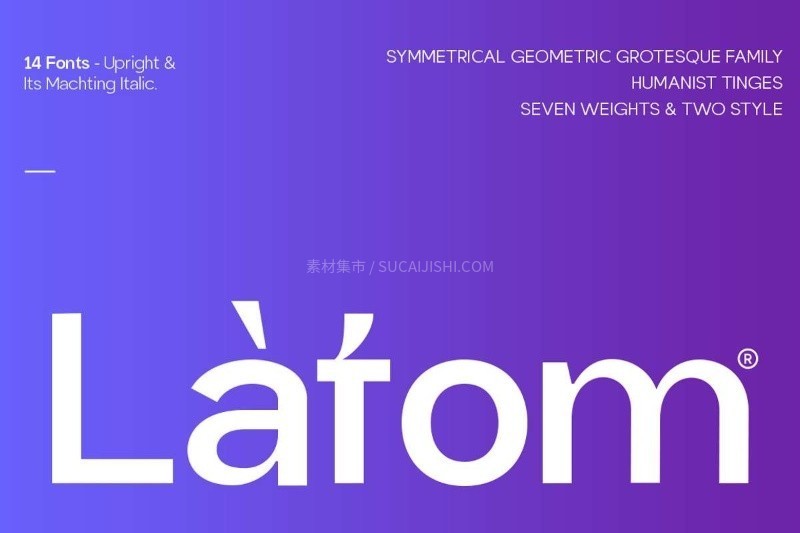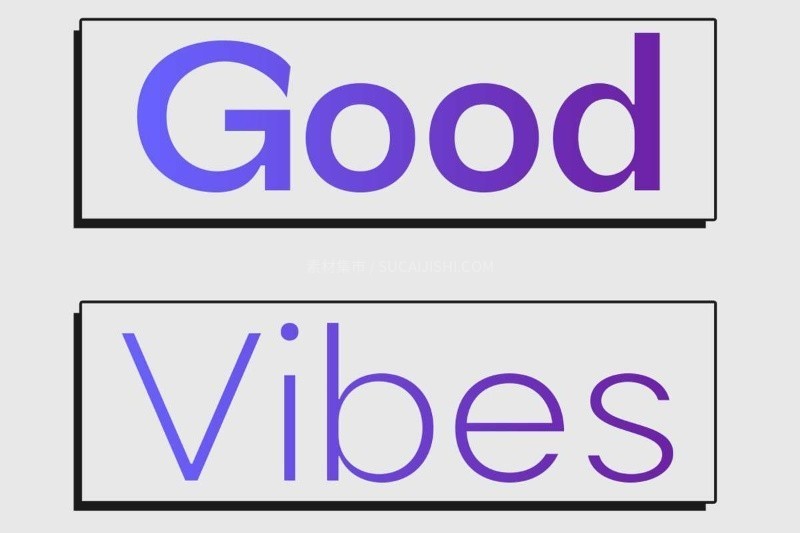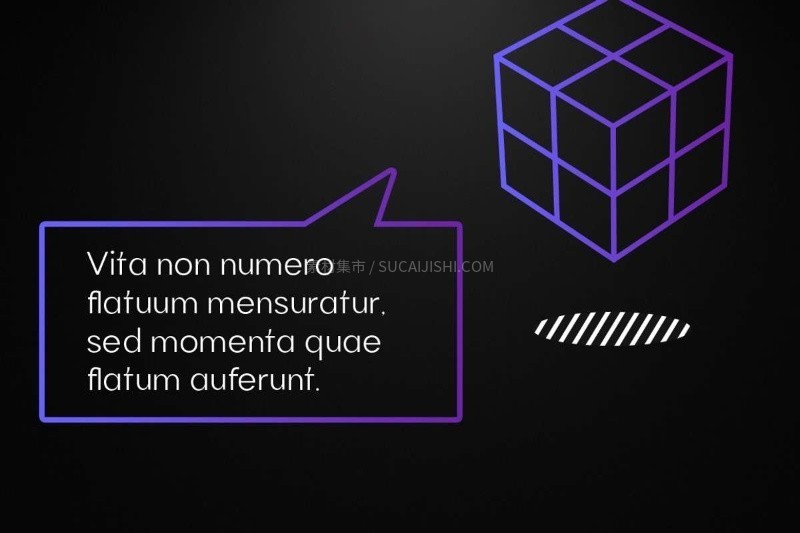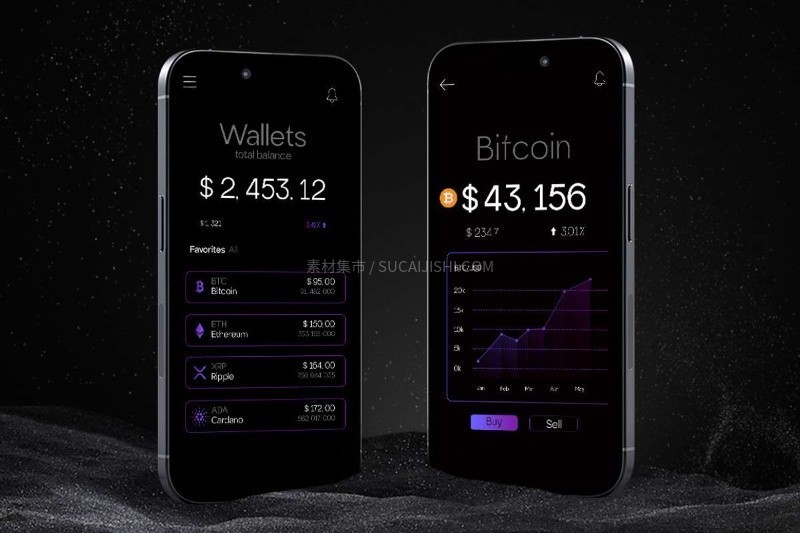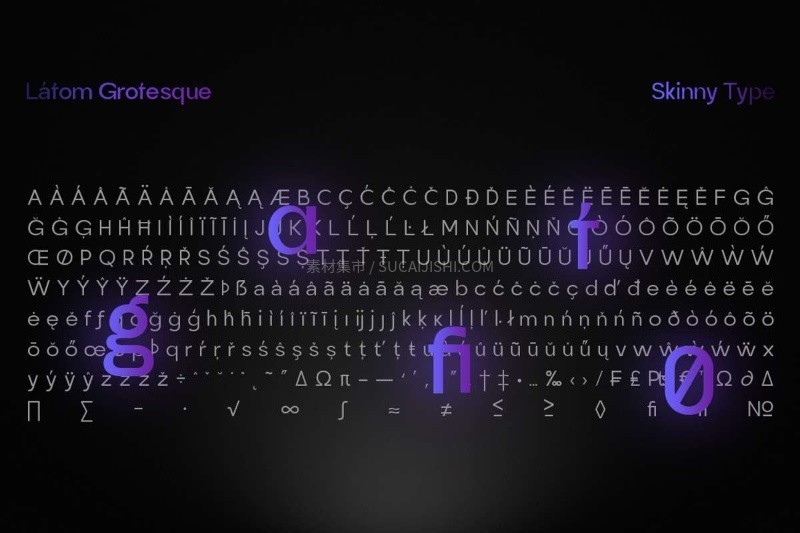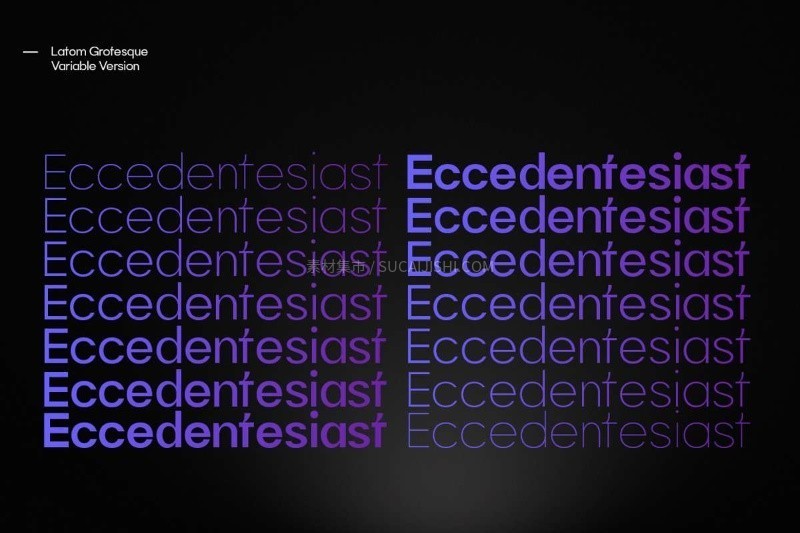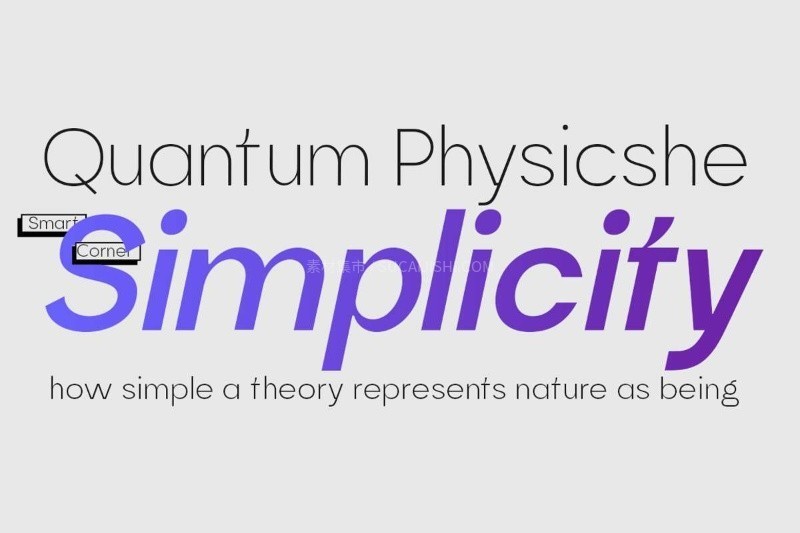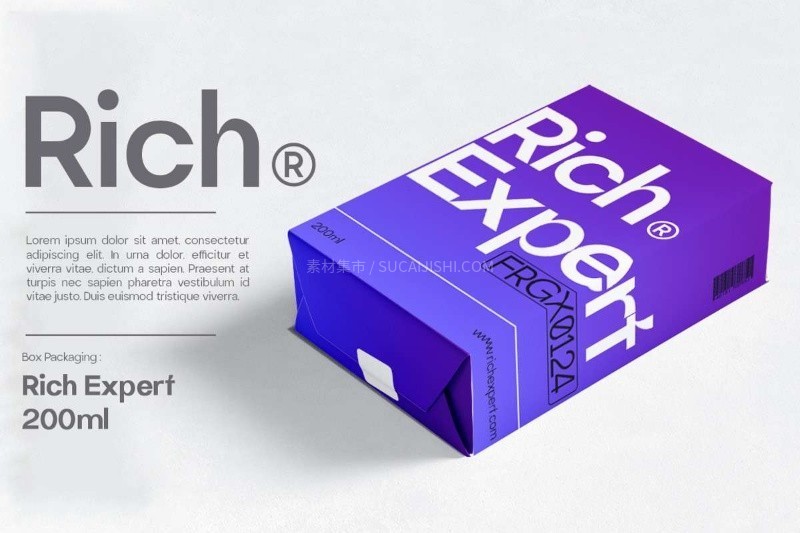
Latom Grotesque 高端品牌英文字体完整版
Latom Grotesque 是一款全面的无衬线字体,包含 7 种不同的字重,从细到粗,搭配相应的斜体,总计 14 种样式,为您提供了极大的设计灵活性。这款字体以其酷炫而纯粹的外观为特点,简洁的几何图形中融入的细微差别。无论是用于高端品牌、醒目标题,还是日常排版,Latom Grotesque 都能完美契合您的需求,提升设计品质。